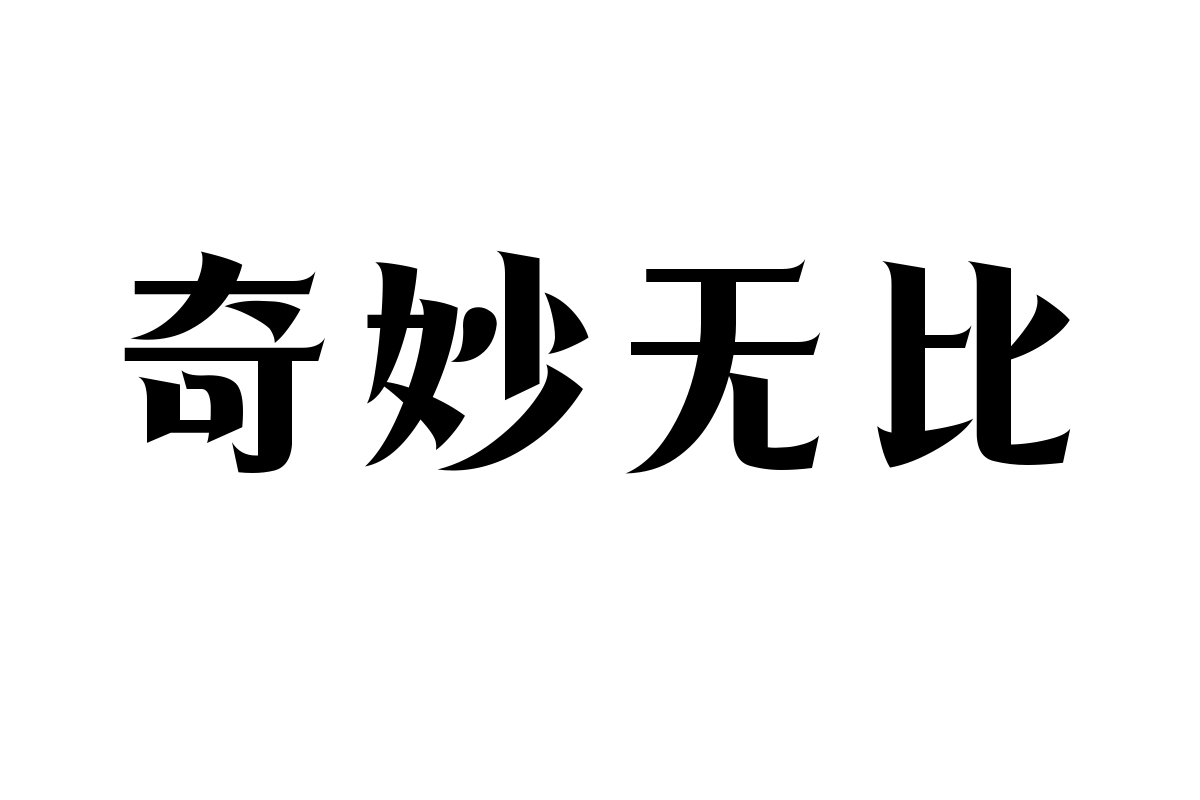
造字工房风舞体是一款现代简约风格的中文字体,由造字工房设计团队精心打造。这款字体具有独特的风格和特点,适用于各种需要展现现代感和简洁美感的场合。
造字工房风舞体字体特点如下:
1. 字形流畅:该字体的笔画线条流畅自然,给人一种轻松愉悦的感觉。
2. 风格简约:字体整体风格简约,没有过多的装饰元素,适合用于需要突出简洁美感的场合。
3. 可读性强:字体结构清晰,笔画间距适中,易于阅读和识别。
4. 适应性强:该字体适用于各种需要展示现代感和简洁美感的场合,如广告、海报、网页等。
总之,造字工房风舞体是一款现代简约风格的中文字体,适合用于需要展现现代感和简洁美感的场合。